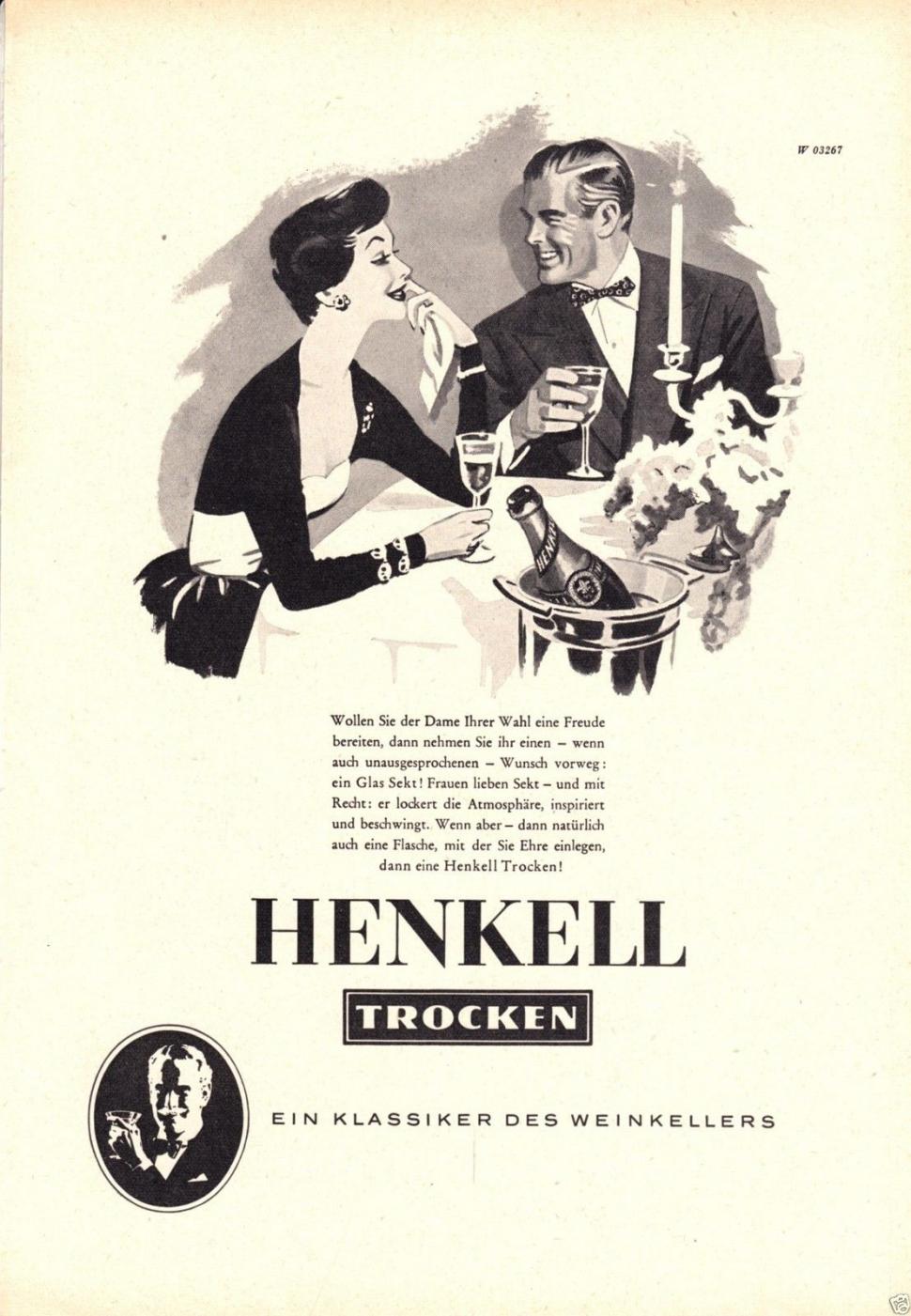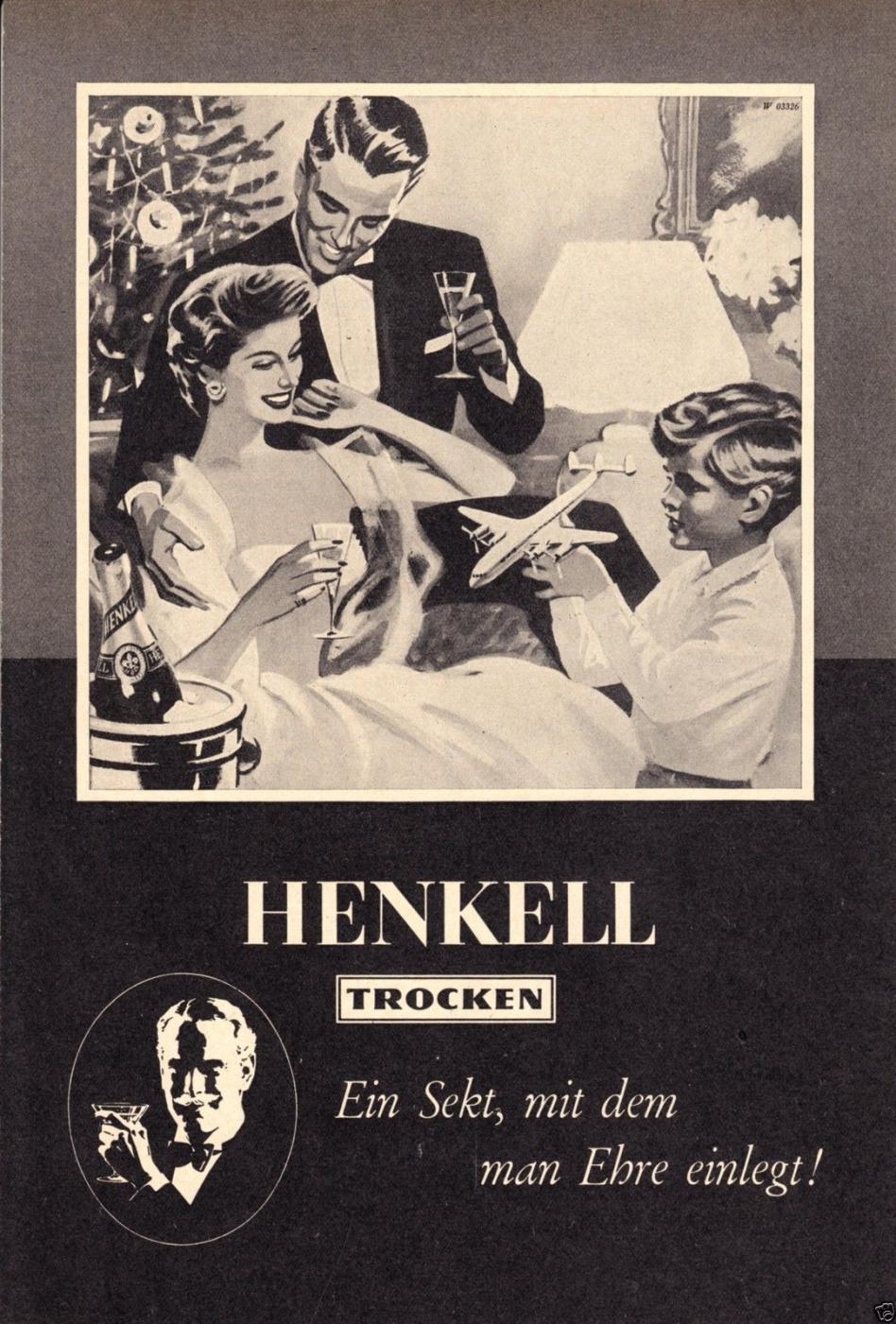
Welche Schrift ist das? (Henkel Trocken)
Ich bin gerade dabei ein Modell von einer alten Henkell Sektflasche zu bauen. Gerade stehe ich völlig auf dem Schlauch. Wisst ihr in welcher Schriftart das Wort TROCKEN geschrieben wurde. Es muss eine Serifenlose mit unterschiedlichen Strichstärken sein. Die Schriftart muss vor 1950 erschienen sein. Könnt ihr mir helfen? Danke.
Vermutlich wurde die Schrift im Negativbalken speziell für dieses Inserat gezeichnet. War zu dieser Zeit nicht unüblich.
Gab’s auch in der positiven Darstellung … auffallend ist der längere mittlere Arm des E.